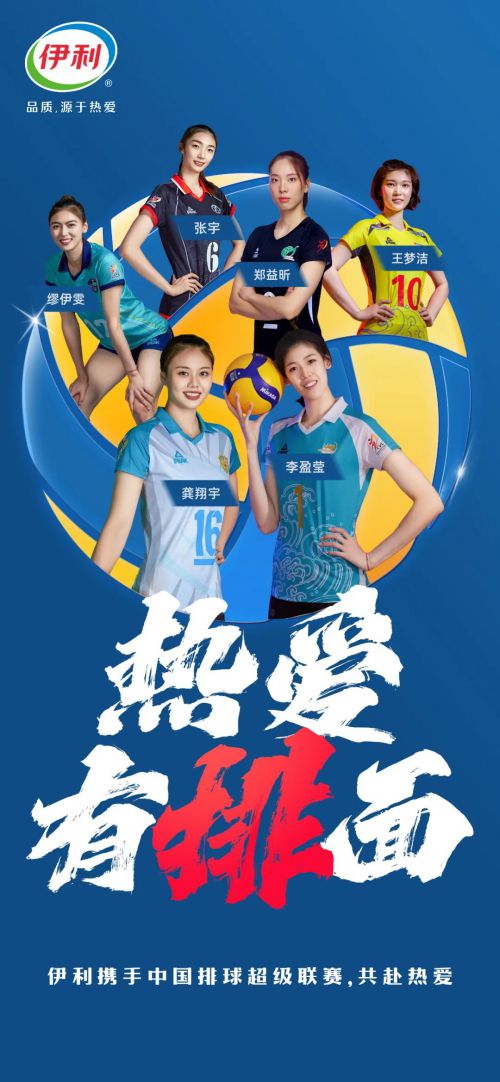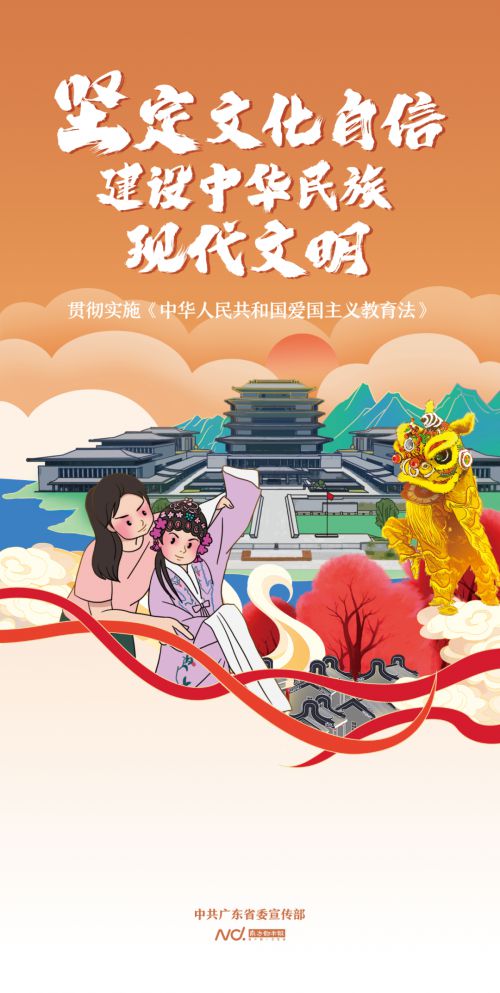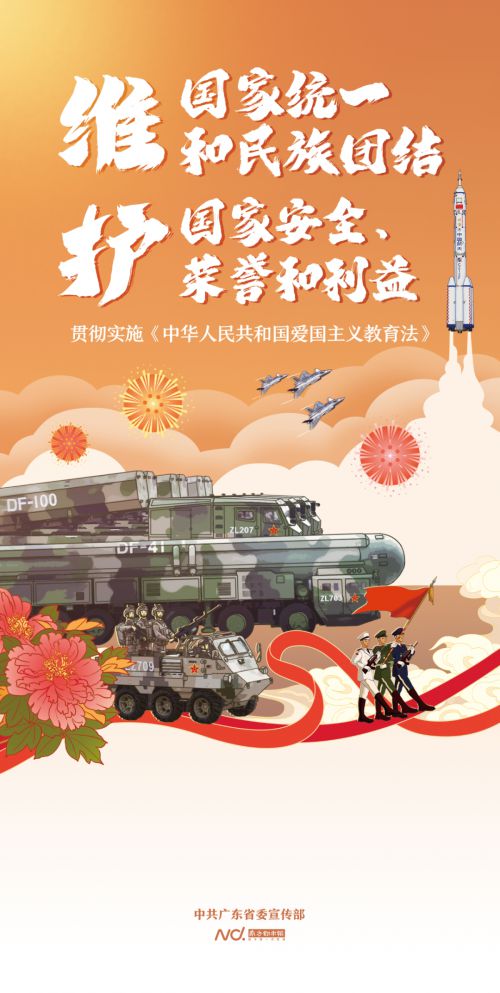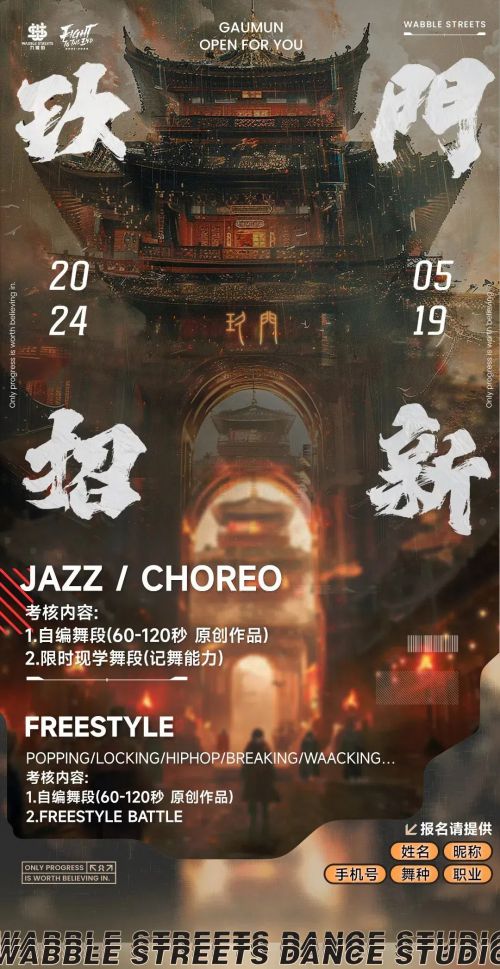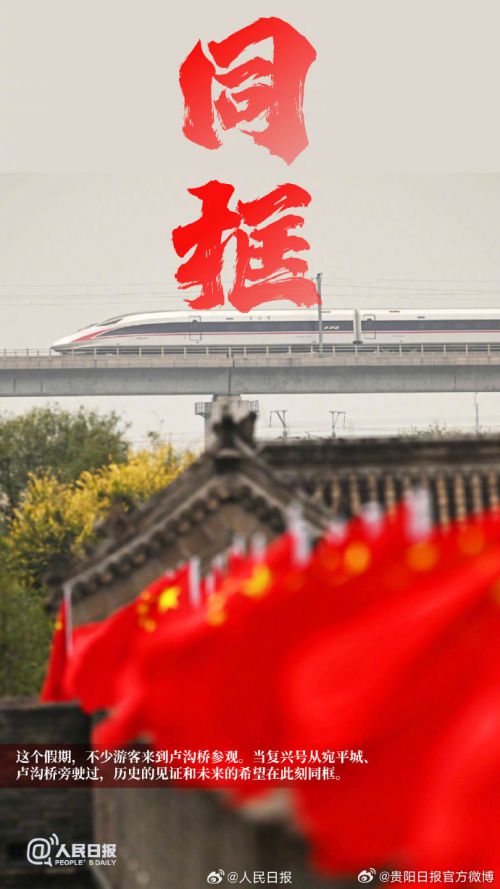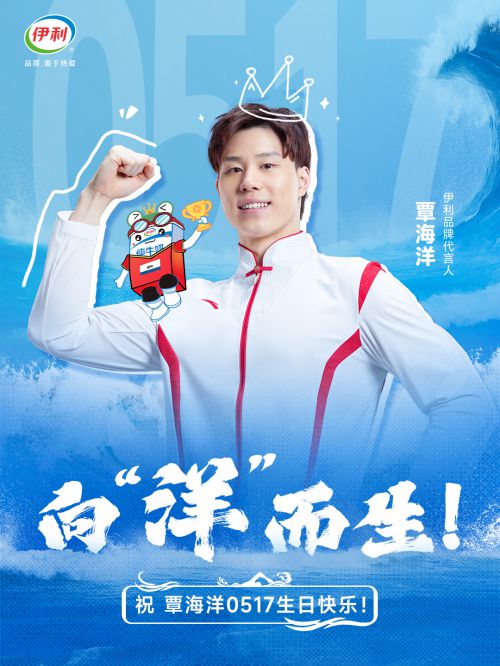
点字苍穹体
点字苍穹体起笔多藏锋,古朴内敛;转折硬朗,饱含碑石意趣;牵丝自然巧妙,增添字体灵动性;墨迹的急徐浓淡变化,彰显收放自如的笔法;点字苍穹体结体平整中见险绝,圆润中见锋芒,内容丰富,耐人寻味。苍穹体毫不掩饰的飞白与毛边,豪迈粗旷,气吞山河,意在表现出毛笔字区别于其他印刷字体的独领风骚的质感。